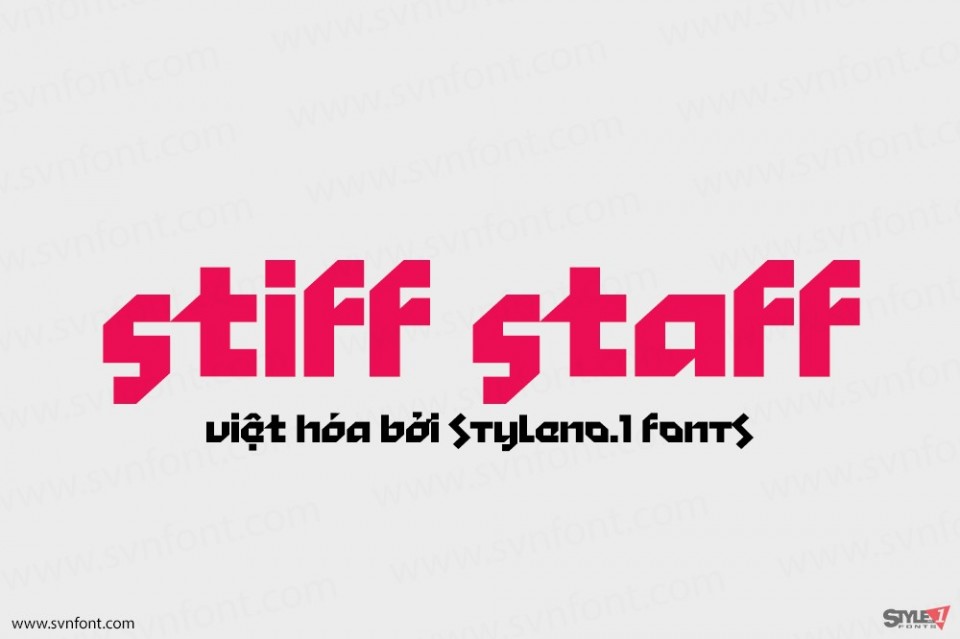
Font việt hóa SVN Stiff Staff
Giới thiệu về Font việt hóa SVN Stiff Staff
Trong thế giới đồ họa hiện đại, việc lựa chọn Font Miễn Phí phù hợp đóng vai trò quan trọng giúp truyền tải thông điệp hiệu quả. Font việt hóa SVN Stiff Staff là một bộ font chữ trang trí độc đáo, mang phong cách hình học mạnh mẽ nhưng không kém phần tinh tế. Được thiết kế bởi Slava Antipov và việt hóa bởi đội ngũ SVN, bộ font này nhanh chóng trở thành lựa chọn ưu tiên cho các bạn học sinh, sinh viên và giáo viên khi thực hiện các dự án thiết kế sáng tạo trong nhà trường.
Đặc điểm nổi bật của bộ Font việt hóa SVN Stiff Staff
Thiết kế hình học tối giản và hiện đại
Đặc trưng lớn nhất của Font việt hóa SVN Stiff Staff chính là cấu trúc các nét chữ được xây dựng từ những khối hình học cơ bản. Điều này tạo nên vẻ ngoài cứng cáp, gọn gàng và rất dễ nhìn. Khi áp dụng vào các bài thuyết trình hay báo cáo học tập, font chữ này giúp nội dung trở nên chuyên nghiệp và hiện đại hơn hẳn các font truyền thống. Từng đường nét được chăm chút kỹ lưỡng để đảm bảo tính thẩm mỹ cao nhất.
Khả năng hiển thị và tính đa dụng
Mặc dù thuộc nhóm font trang trí, nhưng Font việt hóa SVN Stiff Staff lại có khả năng hiển thị cực tốt trên cả màn hình kỹ thuật số lẫn bản in. Các ký tự tiếng Việt được xử lý dấu thanh khéo léo, không bị lỗi font hay chồng chéo nét, giúp người dùng hoàn toàn yên tâm khi soạn thảo. Bạn có thể sử dụng font này để làm tiêu đề báo tường, thiết kế bìa sách hoặc tạo các mẫu poster cổ động trong khuôn viên trường học.